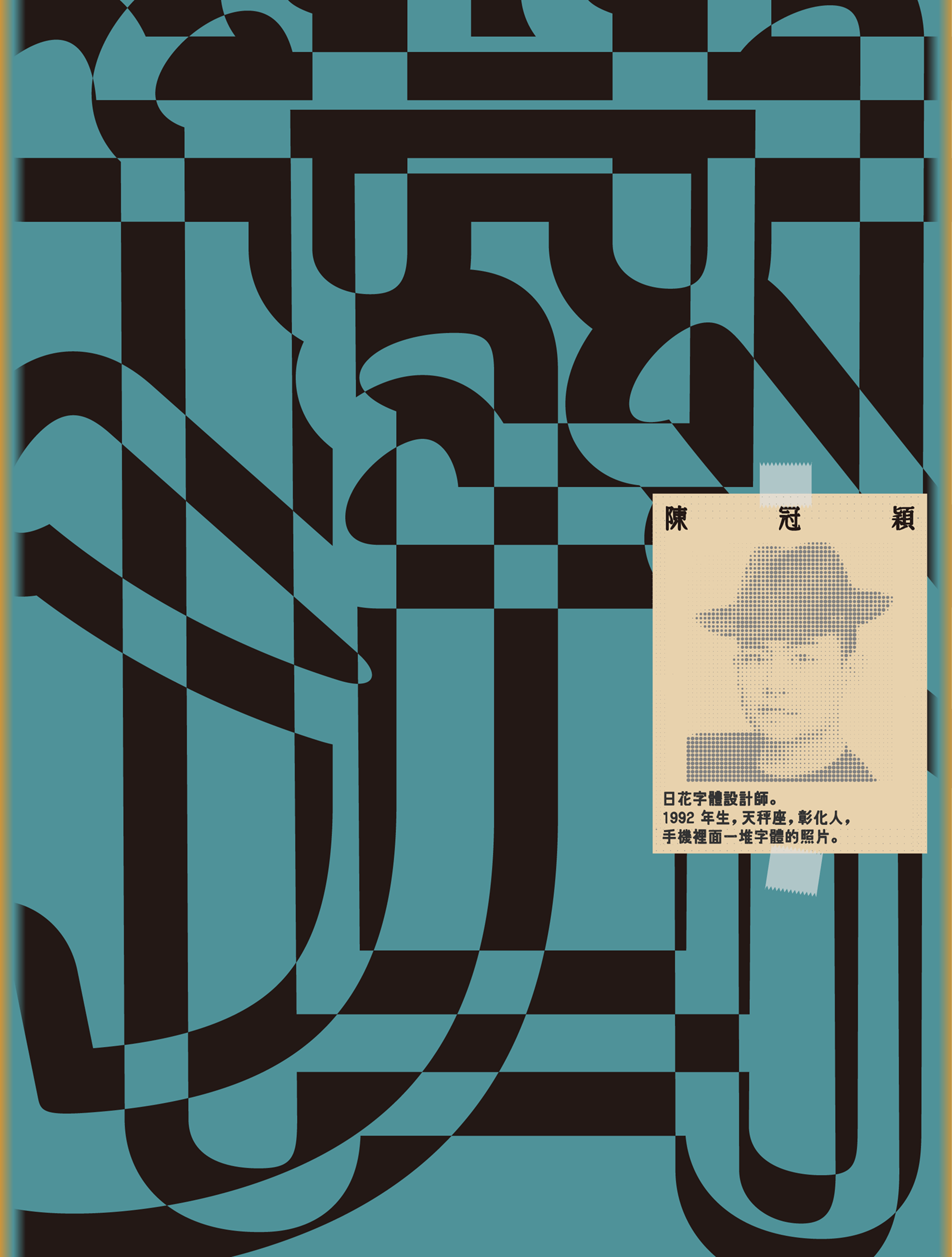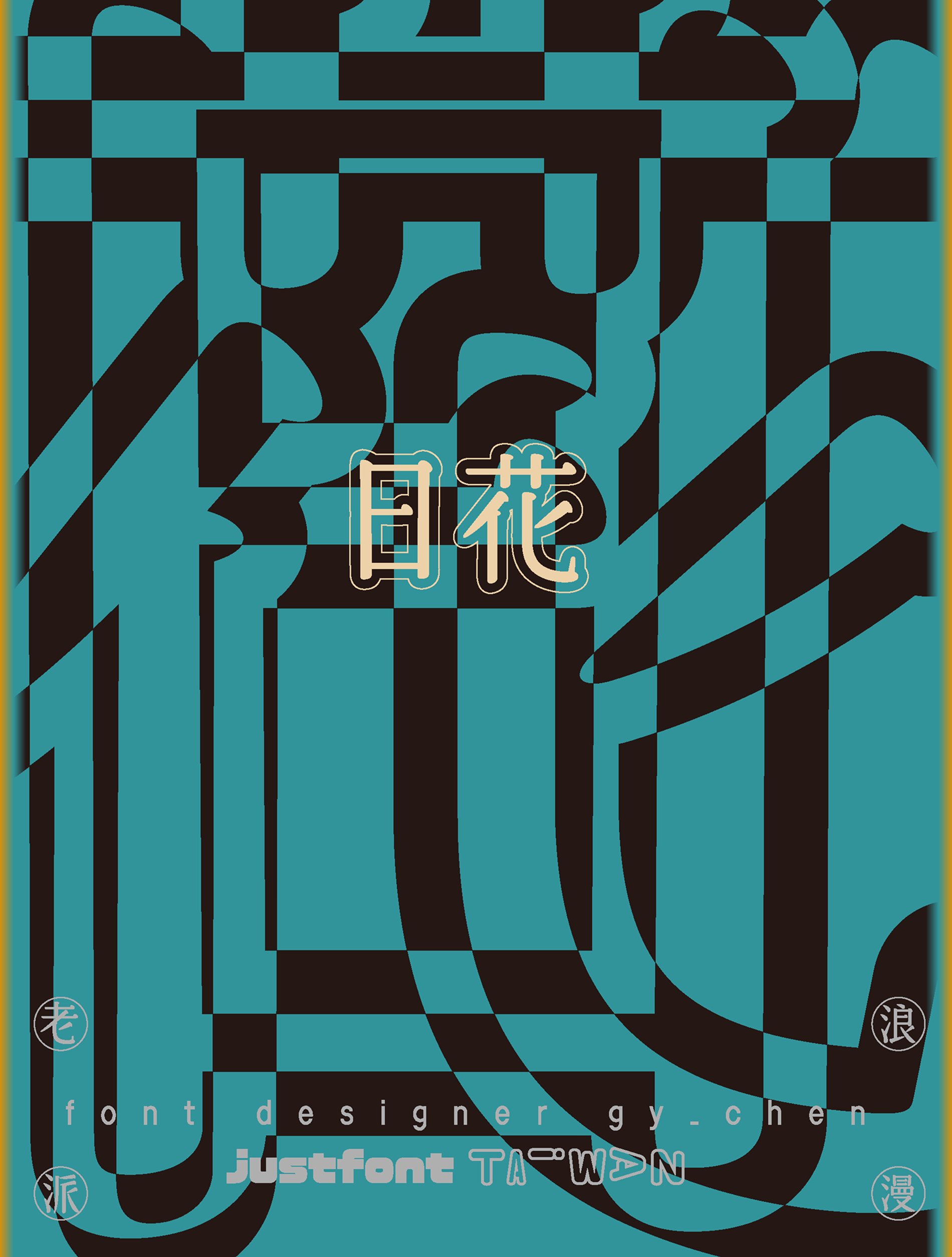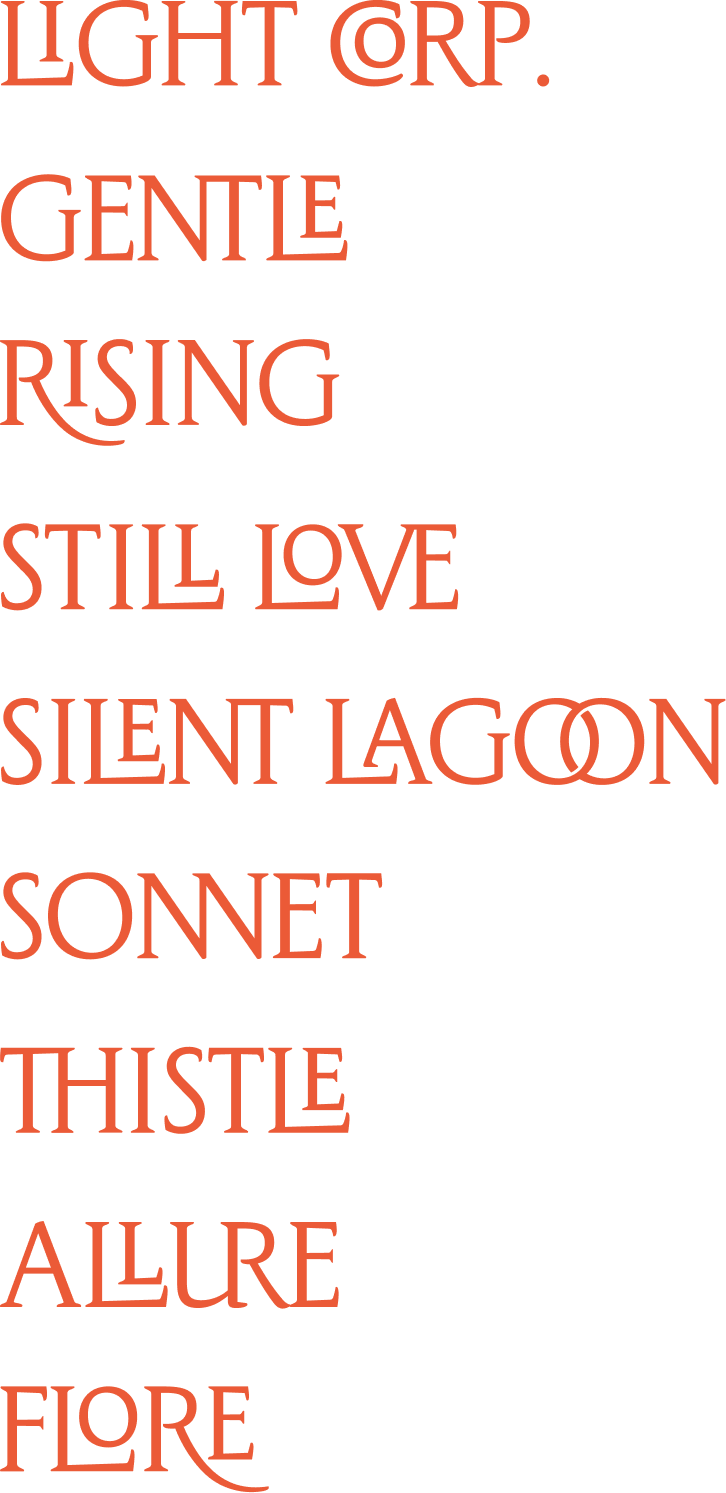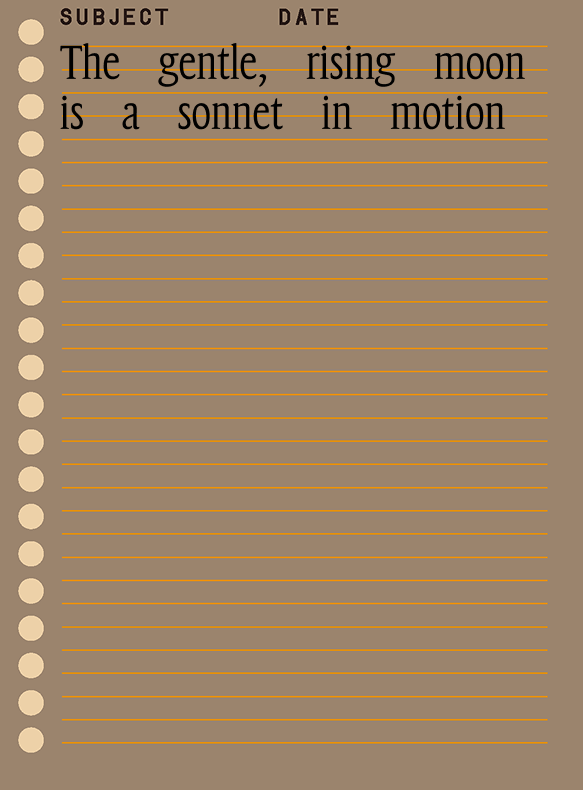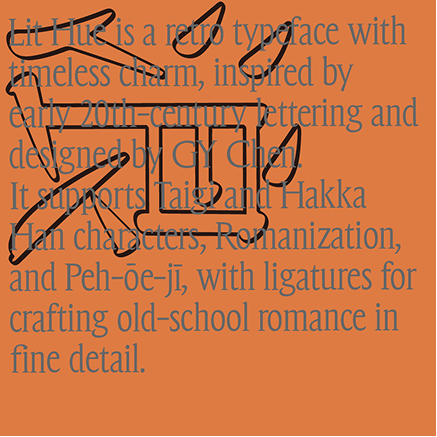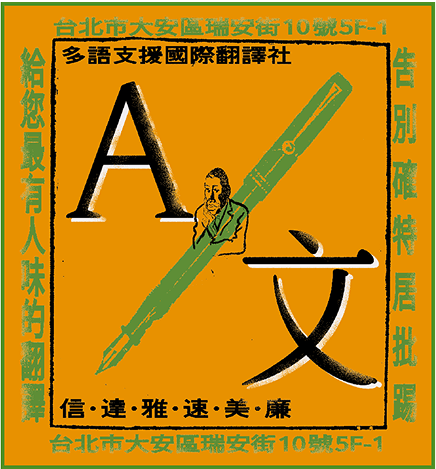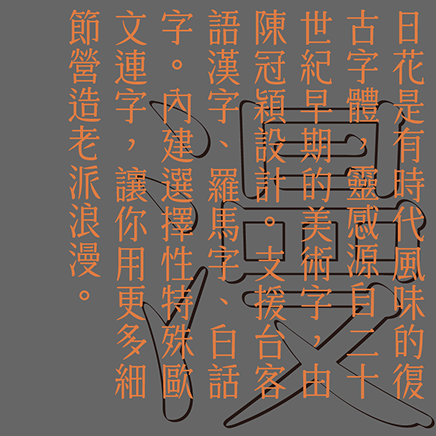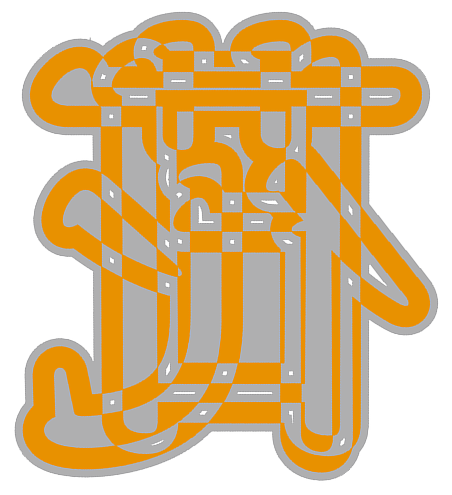
日花
似乎見過你,在某個時代
多語支援:
老派浪漫現代手段
只用一個字型,就能支援漢字、歐文、
數字、台、客語漢字、羅馬字、原住民族語,
還有日文假名跟粵語常用字⋯⋯
這在古早年代是辦不到的。
但日花符合 jf7000 字集,以上都有做到 。
揣一个無人熟似
tshē tsi̍t-ê bô-lâng si̍k-sāi
生份的所在
tshinn-hūn ê sóo-tsāi
燒酒一杯兩杯三杯
sio-tsiú tsi̍t-pue nn̄g-pue sann-pue
當做是笑詼
tòng-tsuè sī tshiò-khue
無聊的祝福
bô-liâu ê tsiok-hok
這馬我無想欲講
tsit-má guá bô siūnn-beh kóng
只想欲離開怹兩个
tsí siūnn-beh lī-khui in nn̄g-ê
有味道的字
新舊交融的摩登感,
把作品的深厚韻味帶出來
日花字樣特色:
●非典型的筆畫造型
●手繪字的啟發
●有機的文字輪廓
●腰身設計
風味來自不尋常之處
根據古早匠師的作法,
日花字型中有許多「異體字」。
可輕易選用,讓作品更富趣味。
小細節,營造老派浪漫
歐文部分,結構符合「羅馬比例」,
更有古典、經典的氣息。
其中更有許多「擇性連字」——西方經典的文字裝飾,能營造更富細節的老派浪漫。